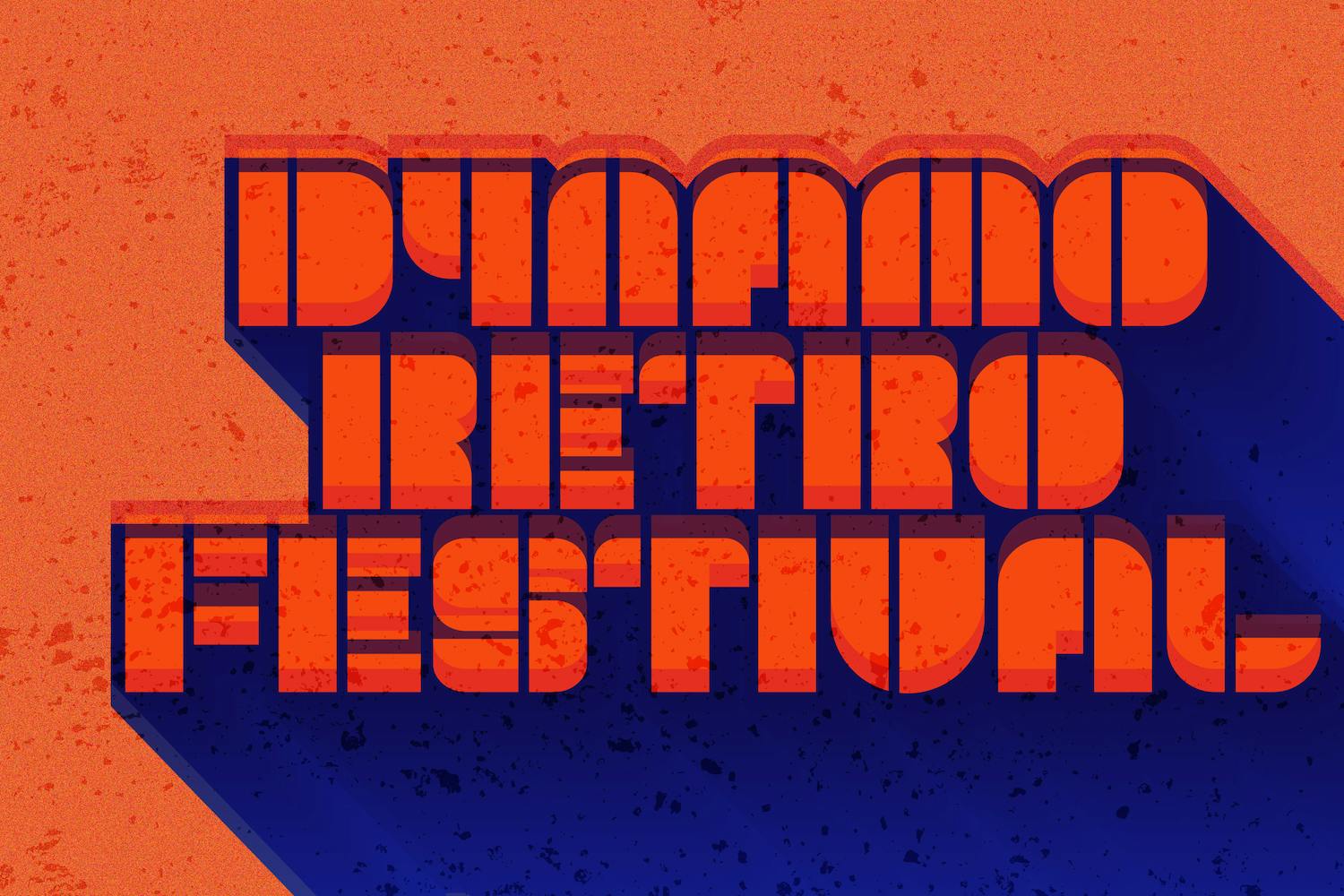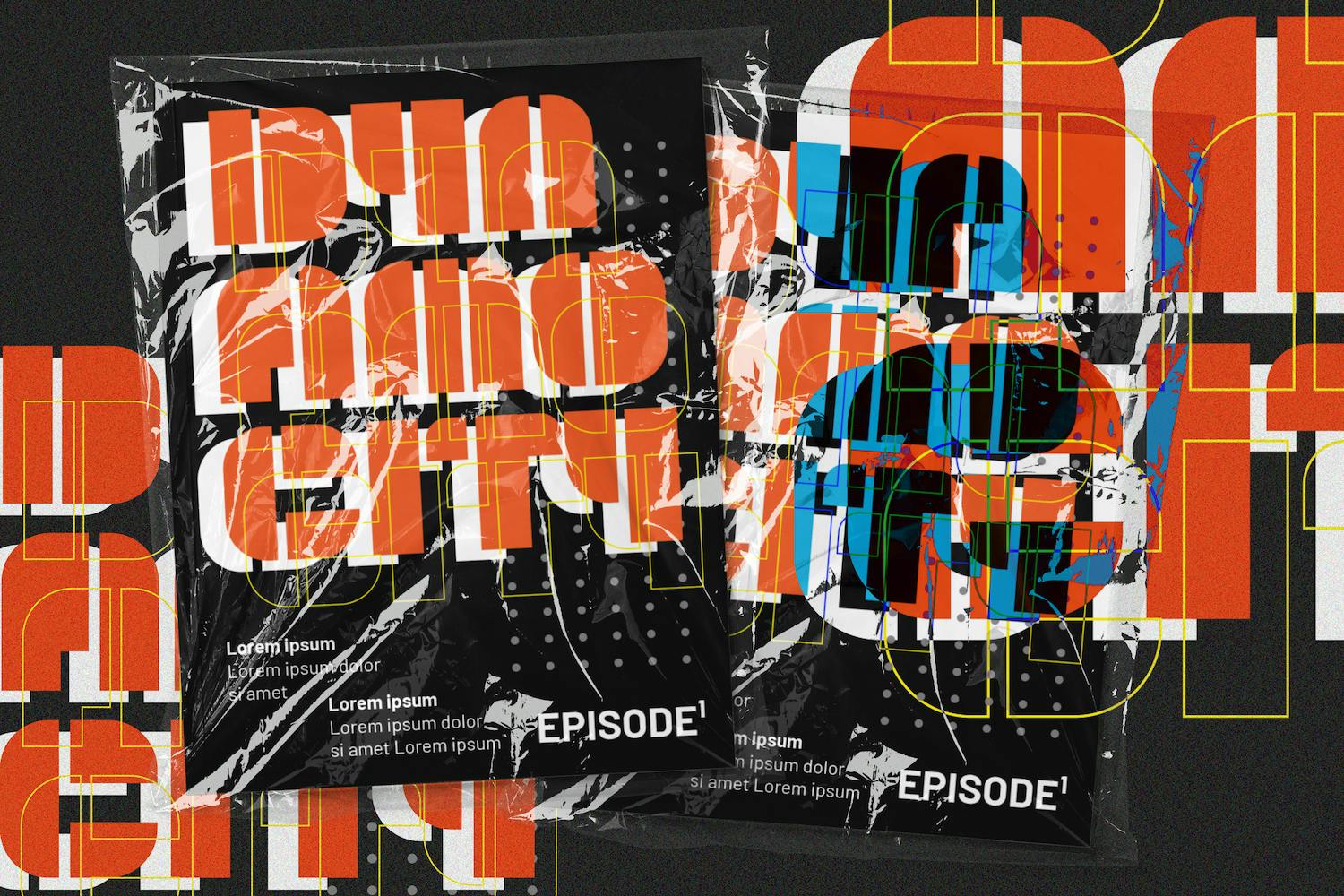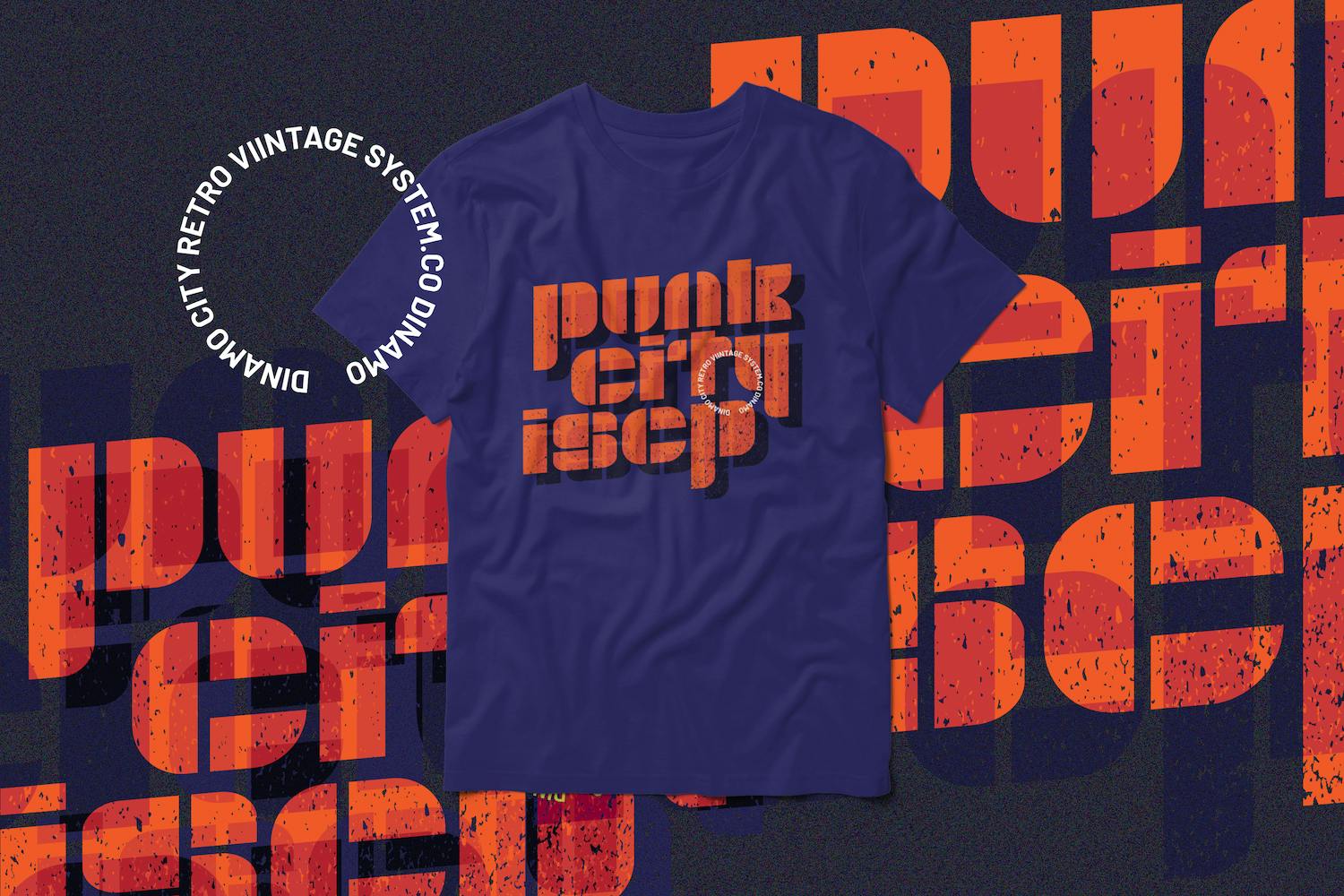
فونت مدرن Monoron مناسب برای طراحی لوگو، برندینگ، کتاب، تیشرت، مجله، برچسبهای بستهبندی و عناوین است. این فونت شامل حروف بزرگ و کوچک، اعداد و نشانهگذاری است و از چند زبان پشتیبانی میکند. با ویژگیهای OpenType، میتوانید آن را با سایر فونتها ترکیب کنید تا طراحیهای شگفتانگیز ایجاد کنید.